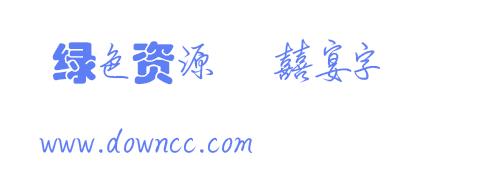
oppo手機字體囍宴體
oppo簡囍宴體是一款十分好看的字體,同時也支持在華為手機上使用在電腦上使用,讓你能夠獲得最精美的字體視覺效果,更有很不錯的視覺風(fēng)格,讓你在欣賞這款字體的同時獲得不錯體驗!
這款字體確實擁有十分精美的行文結(jié)構(gòu),在喜宴上使用將會獲得不粗的效果,如可以運用到喜帖上,十分不錯。